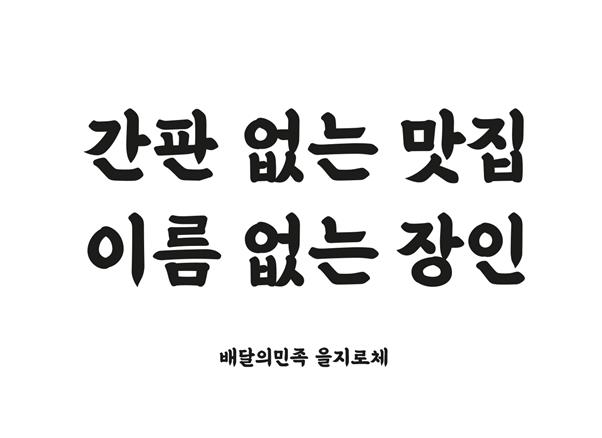
우아한형제들이 2019년 한글날을 맞아 공개한 ‘을지로체’. 우아한형제들 제공 |
‘배달의 민족’을 운영하는 우아한형제들이 한글날을 맞아 8번째 한글 서체 ‘을지로체’를 무료로 공개했다. 우아한형제들은 2012년부터 매해 한글날마다 자체 개발한 무료 한글 서체를 선보이고 있다.
배달의민족 을지로체는 서울 중구 을지로 공구거리 간판에 많이 쓰이던, 간판 장인들이 함석판이나 나무판 등에 붓으로 쓴 글씨를 본뜬 글씨체다. 페인트 붓글씨 특유의 느낌을 살려 획의 시작은 힘차고, 마지막은 부드럽게 마무리된 것이 특징이다. 한명수 우아한형제들 크리에이티브 총괄은 “익숙하고 정감 가는 도시의 풍경을 담은 디자인”이라며 “이름 모를 간판 글씨 장인들의 이야기까지 담아내고 싶었다”고 설명했다.
이번 을지로체는 배달의민족이 배포한 8번째 서체다. 우아한형제들은 한글의 매력을 널리 알리고자 생활 속에서 쉽게 접할 수 있는 간판 글자들을 배달의민족만의 감성으로 재해석해 공개하고 있다. 2012년 한나체를 시작으로 주아체, 도현체, 연성체 등 실용적이고 개성 있는 글씨체들을 다양하게 출시했다. 가장 대표적인 한나체의 경우 이미 출판과 방송, 광고 등 여러 업계에서 널리 이용되고 있어 익숙해진 서체다.